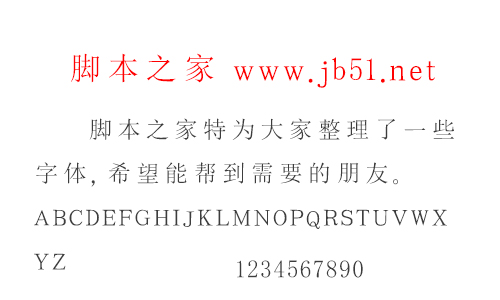
蘭米小標(biāo)宋是蘭米字庫(kù)推出的一款小標(biāo)宋字體,此字體為簡(jiǎn)約的黑白色體,客觀、雅致、大氣、通用,包含簡(jiǎn)體字及符號(hào)合計(jì)7163個(gè),有著宋體字的典型特征,筆畫有粗細(xì)變化,是橫細(xì)豎粗。字體端正清秀,橫輕豎重,結(jié)構(gòu)均勻,筆法嚴(yán)謹(jǐn),美觀實(shí)用。字體非常美觀,適合正文標(biāo)題設(shè)計(jì)使用。歡迎喜歡蘭米小標(biāo)宋字體的朋友前來(lái)下載使用。